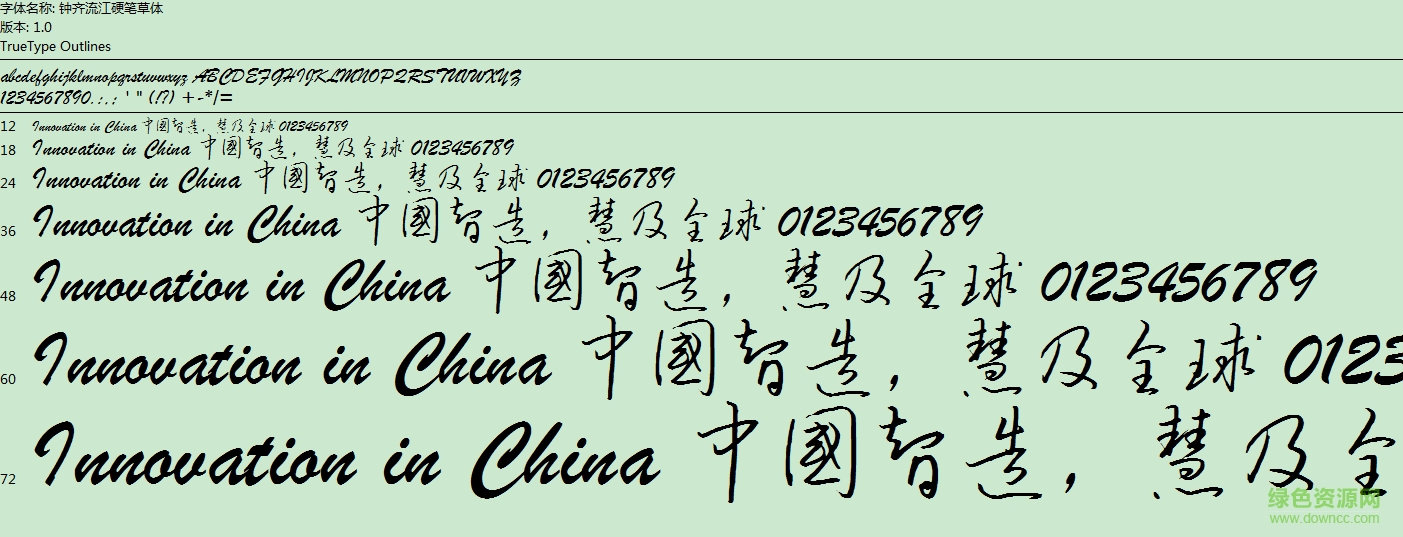
鐘齊流江硬筆草體是一款用于草體書法設(shè)計方面的字體,這款字體剛勁有力,字形瀟灑、不拘一格,并且這款字體的用途非常的廣泛,喜歡的朋友趕緊來綠色資源網(wǎng)下載吧!
圓潤柔美,形神兼?zhèn)?,點畫線條及由此而產(chǎn)生的書法空間結(jié)構(gòu)精巧玲瓏,神采意味綿長,是走進大眾的非常實用書法藝術(shù)。
從整體到局部,再由局部到整體,合理布局,把靜止的形象還原為運動的過程,恰似行云流水,從書法形象到具體形象,創(chuàng)造了作品藝術(shù)新意境,也飽含著作者的文化氣息、人格修養(yǎng)、審美情趣、創(chuàng)作心境和創(chuàng)作目的。